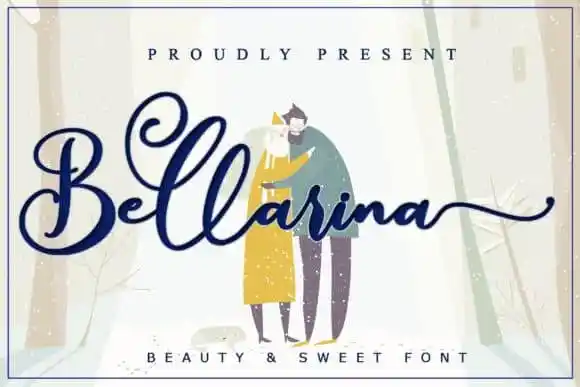
A BellaRina Calligraphy Font é uma criação delicada e elegante do designer aldedesign, ideal para quem busca uma tipografia que ressalta a feminilidade em cada letra. Suas formas bem redondas e distintas criam um estilo versátil e único, fazendo da BellaRina uma fonte perfeita para designers apaixonados por criatividade. Seja para criar gráficos profissionais ou simplesmente amantes de arte digital, a BellaRina é a escolha ideal para tornar seus projetos ainda mais belos e memoráveis. Adquira a BellaRina e comece a explorar uma fonte que vai destacar seu trabalho.